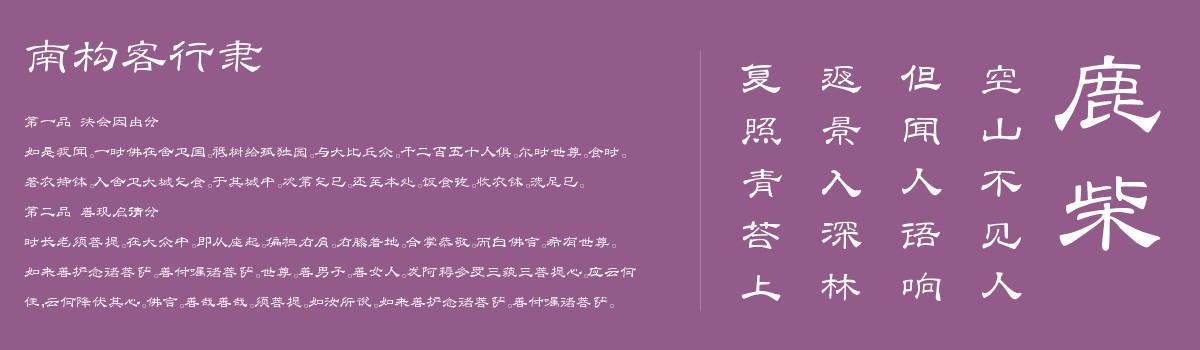
南构客行隶
南构客行隶是一款由字体家AI神笔造字生成的艺术字体。这款字体属隶书风格,字形宽扁如铺开的帛,横向舒展、纵向紧凑。横画是灵魂:起笔似蚕首般圆润饱满,行笔略细,收笔若燕尾轻扬,带优雅波磔;竖画挺直如立木柱,顶端带柔和弧度,不生硬。笔画无尖锐折角,多圆润过渡,线条肥瘦适中,有筋骨的力量感与丝绸般顺滑。整体端庄似古贤端坐,舒展若流云轻拂,稳而不滞、柔而有骨,稳如磐石却透着飘逸。适合用于一些广告标题、平面文案、海报标题、网页广告用字的编辑。